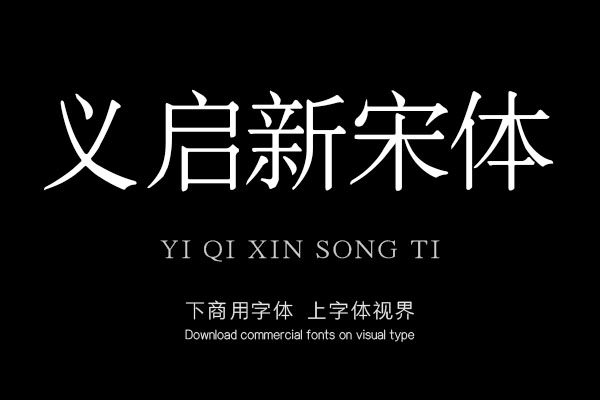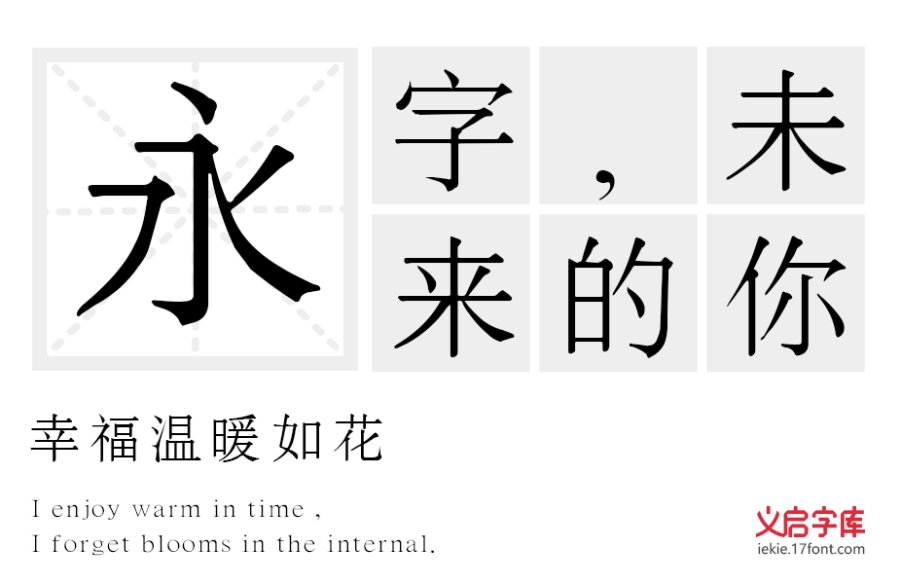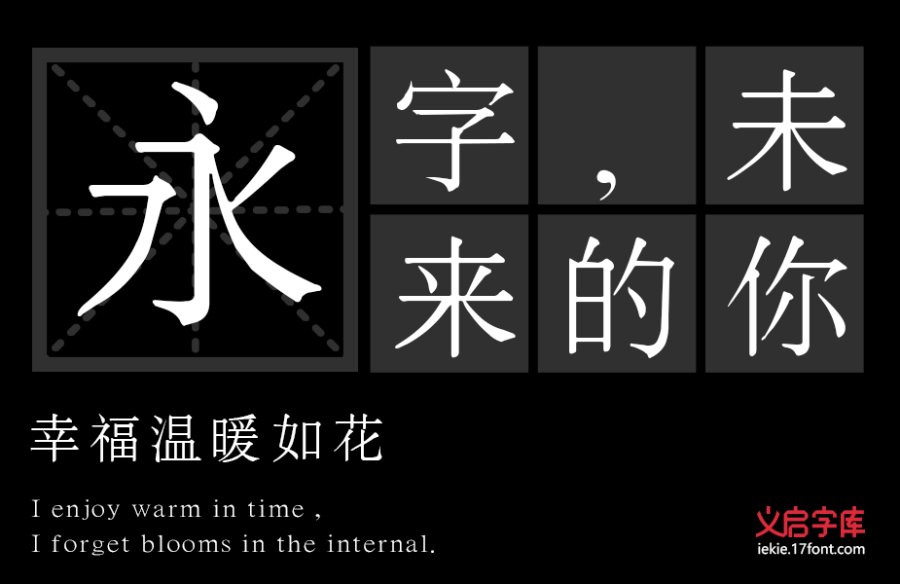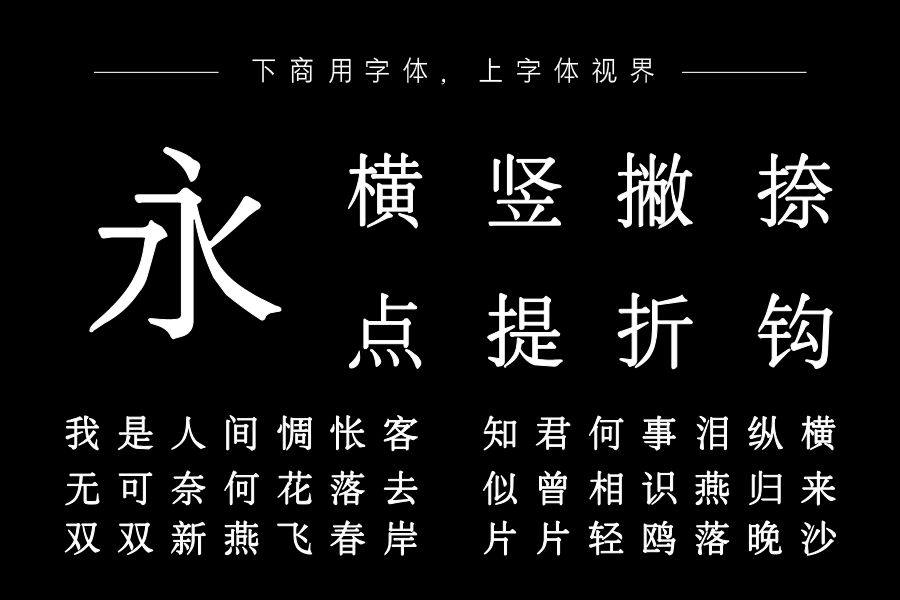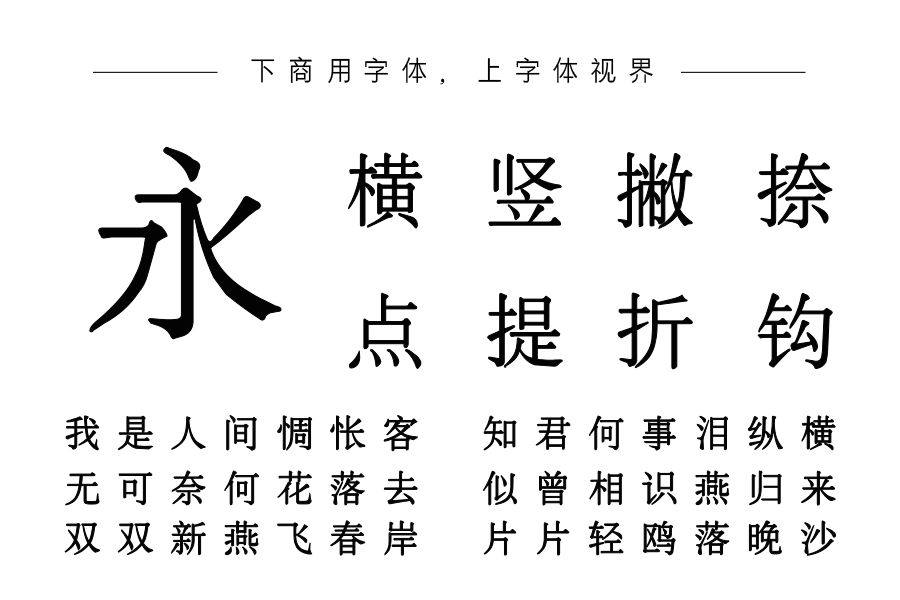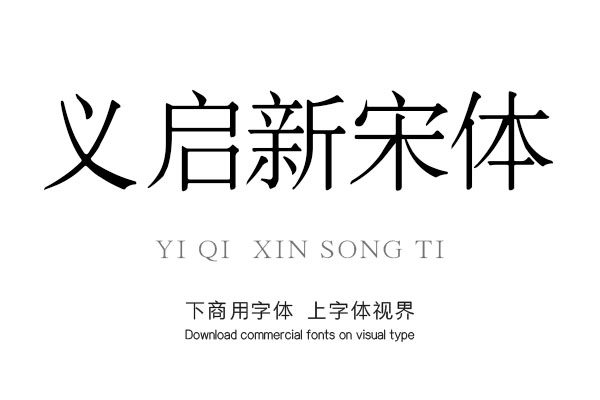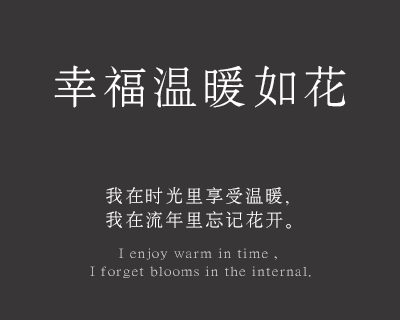
宋体,是为适应印刷术而出现的一种汉字字体。笔画有粗细变化,而且一般是横细竖粗,末端有装饰部分,点、撇、捺、钩等笔画有尖端,属于衬线字体,常用于书籍、杂志、报纸印刷的正文排版。 义启新宋体,在设计上,作者延续了宋体的特色,但宋体毕竟是为了印刷条件而发展传承的,在电子屏幕显示上村在种种弊端,而义启新宋体在继承宋体特性的基础上加大了横笔画的粗度及比例,使得显示更加优化。分享到